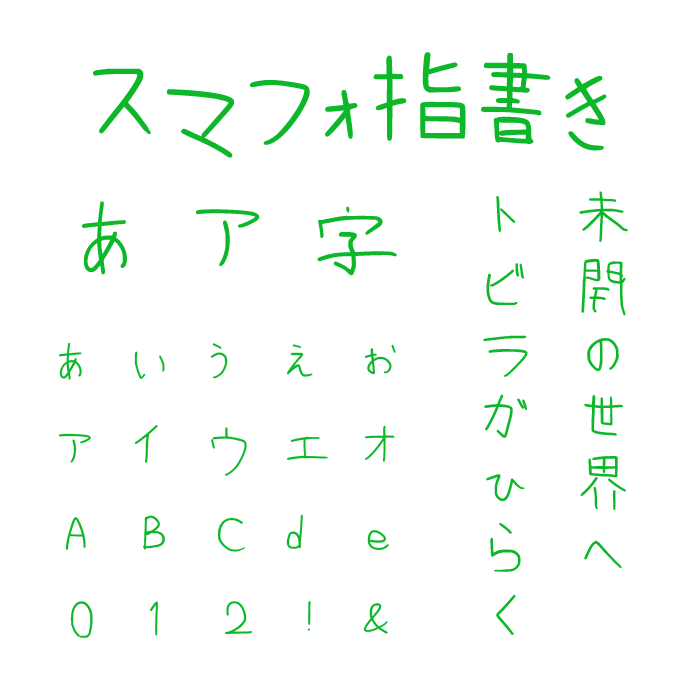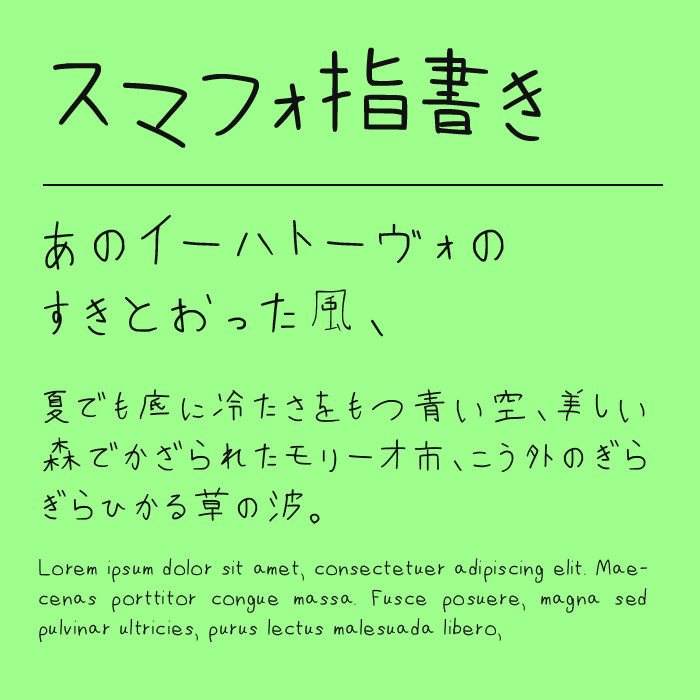
スマフォ指書きフォントは、指先でスマートフォンの画面に直接書いた、ユニークで軽やかな手書きフォントです。
スマフォで指で書いたというプロセスも面白く、絶妙に手崩れすぎずの自然なニュアンスが特徴な文字です。やさしい線の揺れが、カジュアルで親しみやすい印象を与えてくれます。
ラフすぎず整いすぎずの絶妙なバランス感で、日常的な手書きメモやナチュラルなデザインにすっとなじみます。温度感のあるフォントを使いたい場面や、SNS用の画像・配信サムネイルなどに向いています。
収録文字は、漢字・ひらがな・カタカナ・アルファベット・数字・記号が収録。